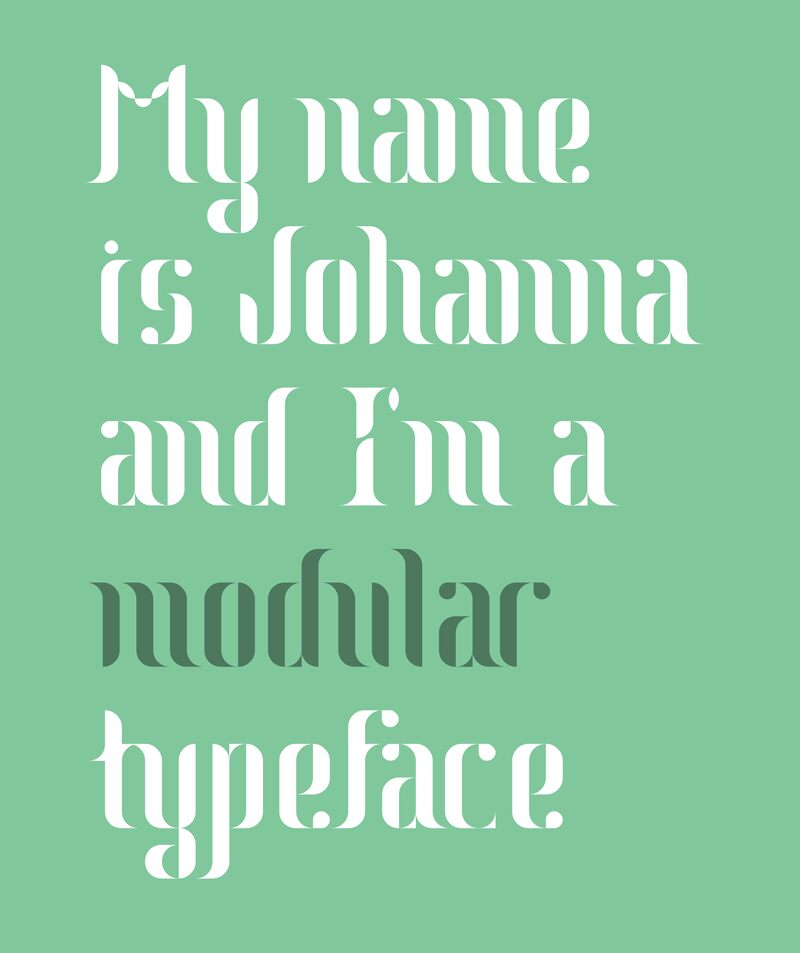
Johanna autorstwa Adrià Gómez to darmowy krój szeryfowy typu retro display o wyrazistym kontraście i szerokich, rzeźbionych krzywiznach. Cienkie włosowate linie spotykają się z solidnymi pionowymi pociągnięciami, a ciasno spasowane litery tworzą gładką, zwartą sylwetkę o wyraźnie modowym charakterze.
Okładki magazynów to jej najsilniejsze środowisko. Tam wyrazista geometria może przekształcić tytuł w centralny element graficzny, a także sprawdza się przy projektowaniu opakowań perfum, identyfikacji wizualnej butików oraz plakatów kulturalnych czerpiących ze stylów edytorskich lat 60. i 70. XX wieku. Liternictwo to najbardziej przemówi do odbiorców z branży mody, urody i sztuki, przyzwyczajonych do eleganckiej, lecz niekonwencjonalnej typografii.
Johanna i Johanna Italic to modularne kroje pism oparte na sześciu podstawowych modułach. Każdy styl zawiera 147 glifów. Są dostępne bezpłatnie.